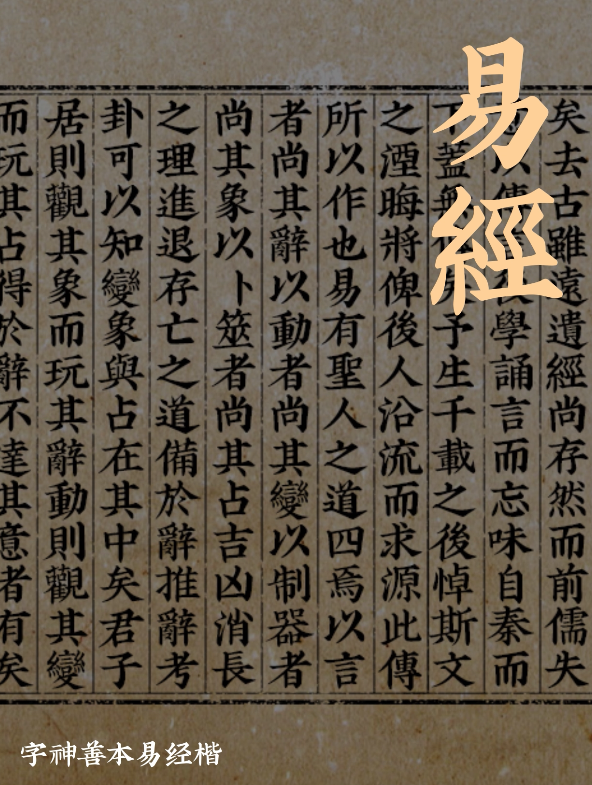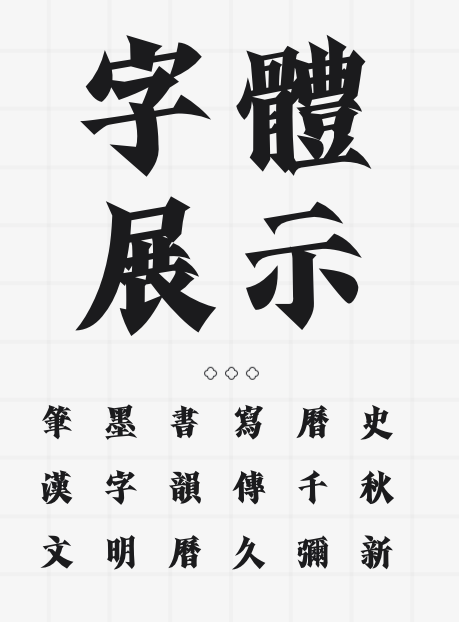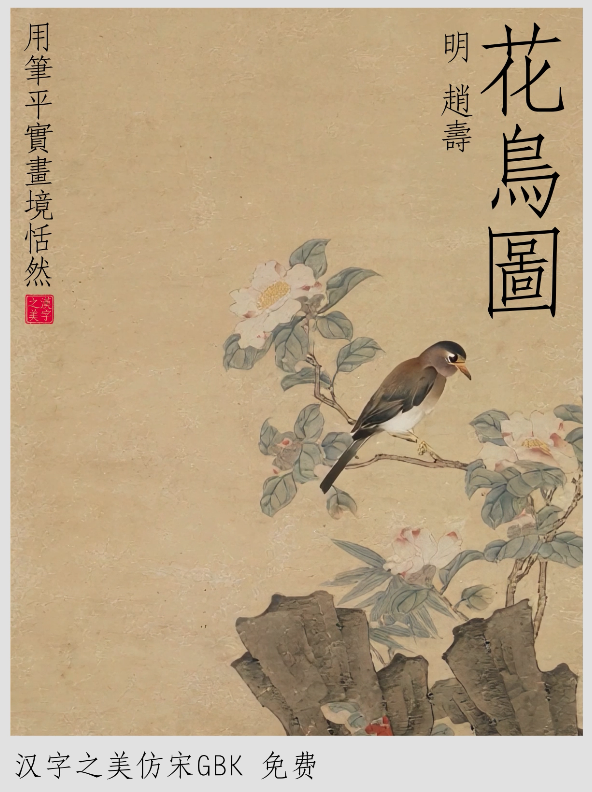
📚书籍装帧新宠儿!这3款字体让你的书页绽放汉字之美✨
书籍装帧,不仅仅是封面设计那么简单,它更是书籍内涵的延伸。而字体,作为装帧设计中不可或缺的元素,更是承载着书籍的气质与灵魂。今天,就为大家推荐三款特别适合书籍装帧的字体产品——汉字之美仿宋、字神善本易经楷和汉字之美涿鹿,让你的书页瞬间焕发独特魅力!🌟
1️⃣ 汉字之美仿宋 —— 古韵悠长,雅致不凡🖋️
仿宋字体,自古以来便是文人墨客的心头好。这款汉字之美仿宋,更是将仿宋的韵味发挥到了极致。它笔画细腻,结构严谨,既有宋体的端庄,又不失仿古的雅致。无论是用于古籍复刻,还是现代文学作品的装帧,都能让书页散发出一种沉静而深远的美感。
2️⃣ 字神善本易经楷 —— 灵动飘逸,气韵生动🌬️
楷体,以其端庄秀丽著称。而这款字神善本易经楷,则在楷体的基础上,融入了更多的灵动与飘逸。它的笔画流畅自然,结构疏密有致,仿佛能够随着文字的节奏起舞。这样的字体,特别适合用于哲学、历史等富有深意的书籍装帧,让读者在字里行间感受到一种气韵生动的力量。
3️⃣ 汉字之美涿鹿 —— 雄浑大气,彰显力量💪
涿鹿字体,以其雄浑大气的风格而著称。这款汉字之美涿鹿,更是将这种风格演绎得淋漓尽致。它的笔画粗犷有力,结构稳健庄重,仿佛能够承载起千年的历史与文化。这样的字体,特别适合用于历史、传记等需要展现力量与厚重的书籍装帧,让读者在第一眼就能感受到书籍的分量与内涵。
三款字体,各具特色,都能为你的书籍装帧增添一抹独特的色彩。快来试试吧,让汉字之美在你的书页上绽放!🌸